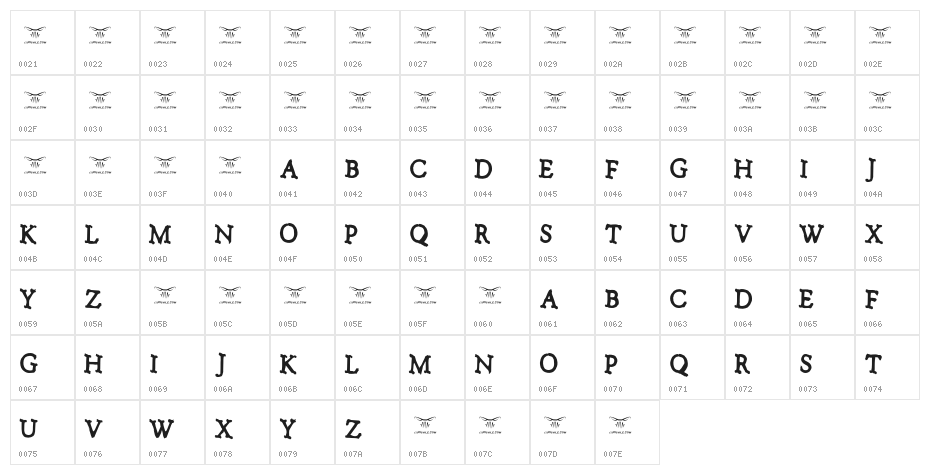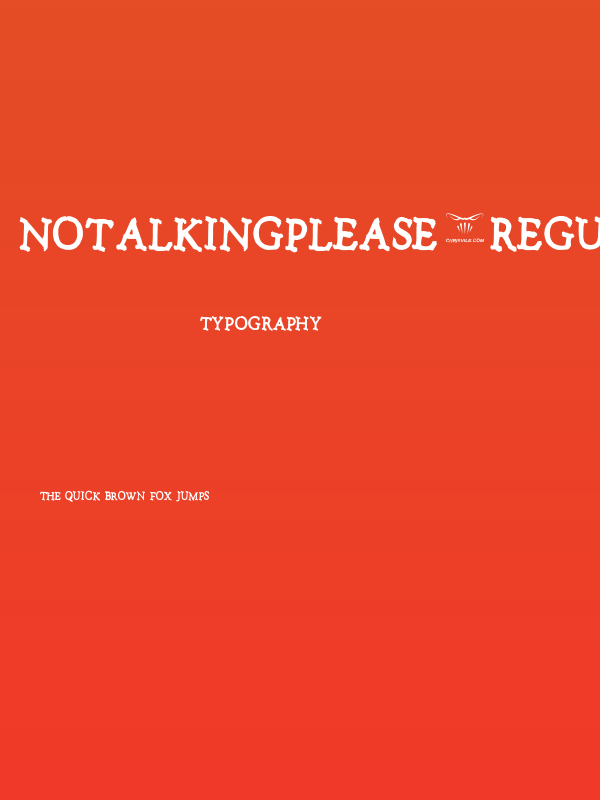
Notalkingplease-Regular Font
| Gesamtstil | Playful, Hand-drawn, Organic |
| Vorgeschlagene Projekte | Perfect for children's books, playful branding, creative posters, and unique invitations. |